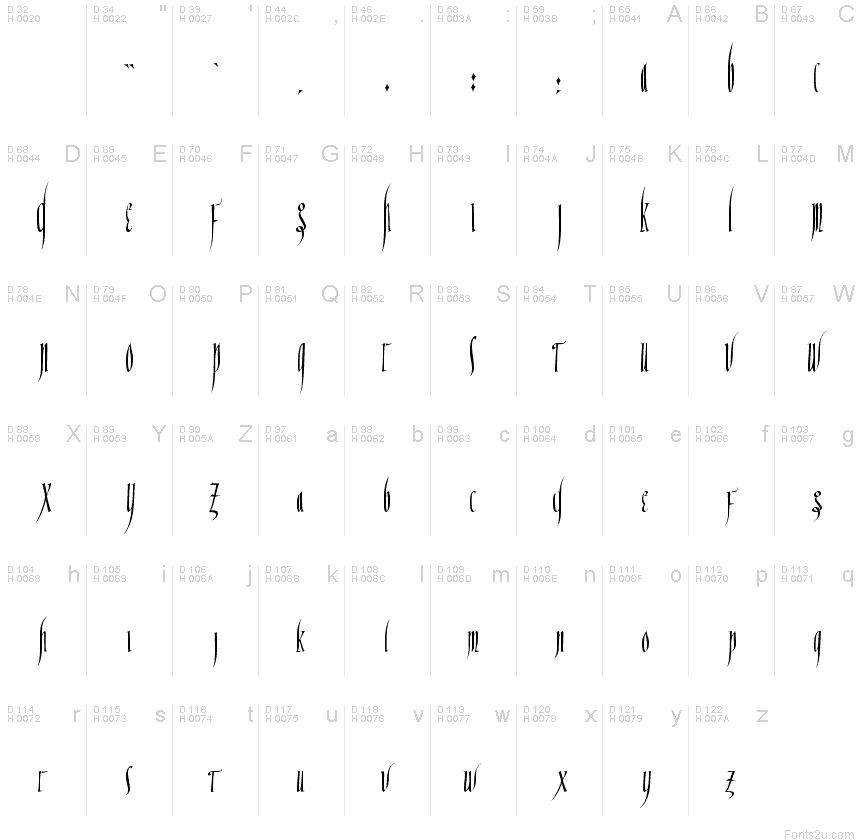
Ranegund, il font gotico merovingio gratuito di David F. Nalle, presenta un ritmo medievale slanciato, caratterizzato da tratti alti e affusolati e terminazioni a uncino. Le lettere richiamano più la scrittura a mano che la solennità cerimoniale; con le loro forme strette, le giunzioni appuntite e una tensione verticale inquieta, questo alfabeto emana un'atmosfera monastica, degna di un antico manoscritto.
Si adatta perfettamente a copertine di libri, poster storici, mappe fantasy, titoli e aperture di capitoli, dove un font gratuito con così tanto sapore d'epoca può fare la differenza con poche parole. Usalo per titoli brevi, iniziali o un branding che cerchi un'estetica europeo-antica, perché quelle lettere lunghe e affilate come lame creano atmosfera ancor prima che il testo venga letto.